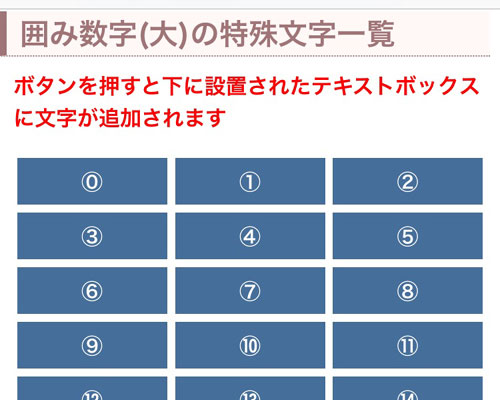
数字フォント一覧!小さい数字やおしゃれな数字をコピペできます
数字フォントにも様々な特殊文字があります。
英語(アルファベット)の特殊文字とは別に数字にも特殊文字が用意されています。
特殊文字の数字は種類としては英語と比べると少ないですが、ちょっとした時に使えるような使いやすいものも多いです。
中でも人気なのは文字にくっついているような小さい数字です。
通常の数字よりも見た目が小さくてかわいいのでちょっとおしゃれな感じにも見せる事ができます。
特殊文字の数字を使いたいけど入力方法がわからないという方もいるようなのでこのページからコピペできるようにまとめました。
色々なパターンの数字を一覧にしてるので参考にして下さい。
数字フォント一覧(コピペ可能な特殊文字)
数字フォントとは、主に以下のようなパターンがあります。
• 小さい数字
• 明朝体の数字
• 太めの数字
• 細めの数字
• 丸囲み数字
• 四角囲み数字
• 白抜き数字
• 丸囲み漢数字
他にもドット付き数字や括弧付き数字などもあったりしますが、よく使う特殊文字としては上記のパターンかと思います。
それぞれの特殊文字について詳しく見ていきましょう。
数字フォント『小さい数字』
特殊文字の小さい数字とは、文字の横に並べると小さく見える数字の事です。
あ¹い²う³え⁴お⁵
A₁B₂C₃D₄E₅
このように、文字の横に小さく数字を入れる事ができます。
上記のように日本語やアルファベットなど、文字の種類に関わらず自由に数字を入れる事ができます。
小さい数字は上に付く数字と下に付く数字の2種類があって、0~9までの数字が使えます。
小さい数字フォント(右上)コピペ
小さい数字フォント(右下)コピペ
数字フォント『小さい数字(特殊)』
小さい数字を使った特殊文字もあります。
他のツールではコピーできないような特殊文字の数字一覧です。
小さい数字フォント(右上・特殊)コピペ
小さい数字フォント(右下・特殊)コピペ
数字フォント『明朝体の数字』
明朝体の数字もオシャレに見えるのでおすすめです。
𝟏𝟐𝟑𝟒𝟓
通常の数字よりも少しスタイリッシュになっているので使える場所も多いです。
数字フォント『太めの数字』
太めの数字を使いたい時にはこの特殊文字を使うのが良いです。
𝟭𝟮𝟯𝟰𝟱
通常の数字より太く表示されるので見やすくなってます。
太さ的には上で紹介した明朝体の数字と近い太さとなってます。
数字フォント『細めの数字』
通常の数字よりも細めの数字を使いたい時に使える特殊文字の数字です。
𝟷𝟸𝟹𝟺𝟻
上記を見ただけでは細くなっているのが少しわかりづらいですが、通常の数字と比べると少しだけ細くなっているのがわかります。
シンプルな数字を使いたい時にどうぞ。
数字フォント『丸囲み数字』
丸囲み数字とは、数字を丸で囲った文字になります。
①②③④⑤
❶❷❸❹❺
このように白丸で囲った数字と黒丸で囲った数字が用意されています。
また、丸囲み数字にはもう少し別の種類も用意されていて、以下のように二重丸で囲った数字もあります。
⓵⓶⓷⓸⓹
これも通常の数字とは違って目立つ特殊文字ですね。
丸囲み数字は白丸と黒丸で使える数字の幅が変わります。
白丸は⓪~㊿まであるのに対して、黒丸は⓿~⓴までしか用意されていません。
そして、二重丸は⓵~⓾までとなります。
数字フォント『四角囲み数字』
四角囲み数字とは、丸囲み数字の四角版です。
通常、四角囲み数字というのは以下のように絵文字で表現されるのが一般的です。
1⃣2⃣3⃣4⃣5⃣
絵文字でも良いのですが丸囲み数字のようにちゃんとした四角で数字を囲みたいというケースもあるでしょう。
そういう時は以下のような数字を使います。
1⃞2⃞3⃞4⃞5⃞
このように丸囲み数字と同じような四角囲み数字を使う事もできます。
また、上記の仕組みを使えば黒丸の囲み数字を四角囲みにしたりなど、通常の数字では存在しない特殊文字を作る事もできます。
❶⃞❷⃞❸⃞❹⃞❺⃞
➊⃞➋⃞➌⃞➍⃞➎⃞
数字フォント『白抜き数字』
白抜き数字とは以下のような特殊文字です。
𝟙𝟚𝟛𝟜𝟝
普通の数字や囲み数字とも雰囲気が違うので、白抜き数字も意外と人気があったりします。
特に数字を目立たせたい時には白抜き数字もおすすめですね。
白抜き数字は0~9までコピペできます。